う奈ぎ(うなぎ)がうふぎに見えて仕方ない。
うなぎがどうしても「うふぎ」に見えてしまうのは、う奈ぎの奈を「変体仮名」で書いた際に「ふ」に見えるという訳です。
変体仮名は平仮名の字体の内、1900年の小学校令施行規則改正以降の学校教育で使用されなくなった字体の総称。うなぎ屋などの一部の看板や書道などではまだ見かけており、異体仮名とも呼ばれています。
うなぎには江戸文字が映えるはず、寄席文字「うなぎ う奈ぎ うふぎ」の文字見本
うなぎには江戸文字が映えるはず、籠文字「うなぎ う奈ぎ うふぎ」の文字見本
うなぎには江戸文字が映えるはず、ひげ文字「うなぎ う奈ぎ うふぎ」の文字見本
うなぎには江戸文字が映えるはず、勘亭流「うなぎ う奈ぎ うふぎ」の文字見本
うなぎには江戸文字が映えるはず、相撲字「うなぎ う奈ぎ うふぎ」の文字見本
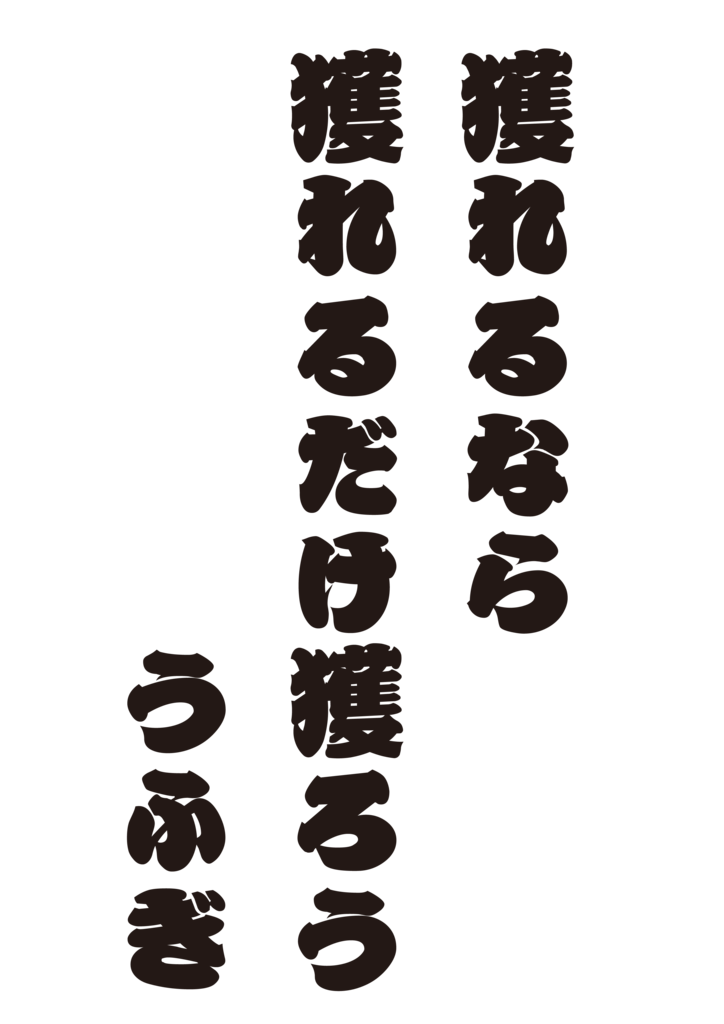
ただし、ニホンウナギは2014年にレッドリストの内、近い将来において野生での絶滅の危険性が高いとされる「絶滅危惧IB類」に追加されており、「取れるなら取れるだけ取ってしまおう、うなぎ」ではいずれ絶滅してしまうのかもしれないが…。